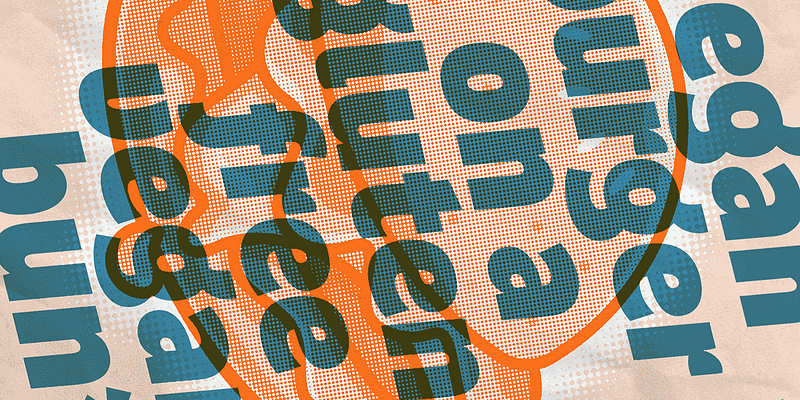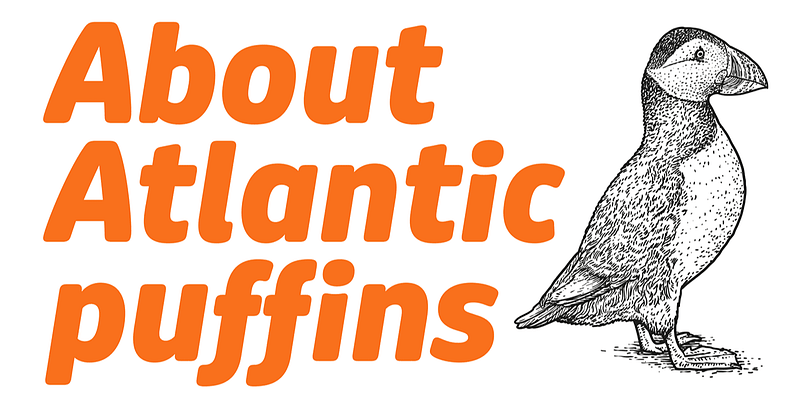
「Bold Monday」の初版リリースの中に、Pieter van Rosmalen の「Pinup」があったことを覚えている方も多いのではないでしょうか。カジュアルで親しみやすいデザインでしたが、スタイルは 1 つだけでした。それから 10 年以上が経ち、その書体は 2 つの充実した書体シリーズ「Puffin」と「Puffin Arcade」に成長しました。1 つは非常に実用的でありながら楽しい書体、もう 1 つは非常に楽しく、かつきわめて実用的な書体です。拡張された「ノーマル」ファミリーは、「Puffin」、「Puffin Display」、「Puffin Display Soft」からなり、それぞれ 7 つのウエイトとイタリック体が用意されています。「Plain Puffin」は最も素朴で、汎用性の高いヒューマニストサンセリフで、ゆったりとした間隔と傾斜の大きいイタリック体 (15°) を持ち、画面上での読み取りやユーザーインターフェイスのデザインに適しています。「Puffin Display」と「Puffin Display Soft」は、それに比べてより味わい深いものとなっています。「Puffin Display Soft」は、特にイタリック体の曲線と丸みを帯びた端末が特徴的で、親しみやすさを感じさせます。一連の「Display」のスタイルは x ハイトが高く、字間がややタイトであるため、中程度から大きめの文字サイズで暖かみが必要なあらゆる用途に適しています。また、ポスターやゲームなど、さらに遊び心を演出する場合は、Puffin Arcade と組み合わせることができます。